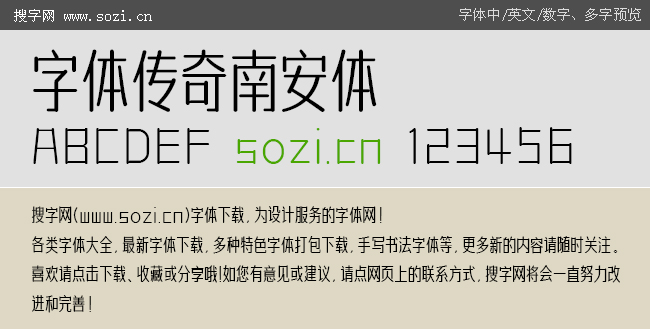
字體傳奇南安體
搜字網(wǎng)給大家提供一款字體傳奇南安體中文字體下載,這款字體由福建南安設(shè)計師吳金彬設(shè)計、字體傳奇編碼完成,為了宣傳設(shè)計師的家鄉(xiāng),故命名南安體,且免費(fèi)供大家使用。這款字體結(jié)合了圓黑與宋體兩種字體的特點(diǎn),所以既優(yōu)雅又簡潔、既柔和又時尚,適合應(yīng)用于藝術(shù)設(shè)計、平面宣傳設(shè)計、網(wǎng)頁設(shè)計、海報設(shè)計等應(yīng)用。